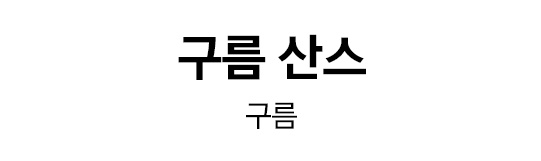
여유로운 골격과 정원에 가까운 자소 ㅇ의 형태로 젊고 모던한 인상을 주며,세 가지 웨이트로 제작되어 여러 매체에 사용할 수 있습니다.
| 프로젝트명 | 구름 산스 / 구름 산스 코드 |
디자인용 3종 : 유니코드(한글 11,172자 + 영문 95자 + 약물 986자) 코딩용 1종: 고정폭(영문 95자 + 오픈타입 피처(1,267자) + 리가처) |